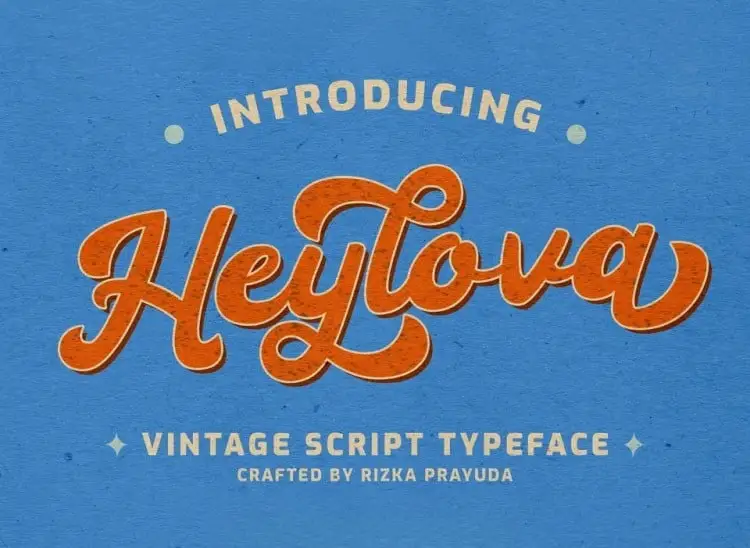
A Heylova Script Font é uma escolha ideal para quem está buscando dar um toque vintage a qualquer projeto. Criada pelo estúdio Atasi Studio, essa fonte script tem um forte tom e diversos alternativos e ligaturas que a tornam perfeita para logotipos, projetos de música, posts nas redes sociais, postais de evento, imagens de marca, embalagens de produtos, citações escritas a mão, merchandising e muito mais. Com sua elegância retrogata, a Heylova tem um visual que combina bem em qualquer projeto visual moderno. Não hesite em entrar em contato caso tenha alguma dúvida ou não saiba como usar a fonte para seu projeto específico.